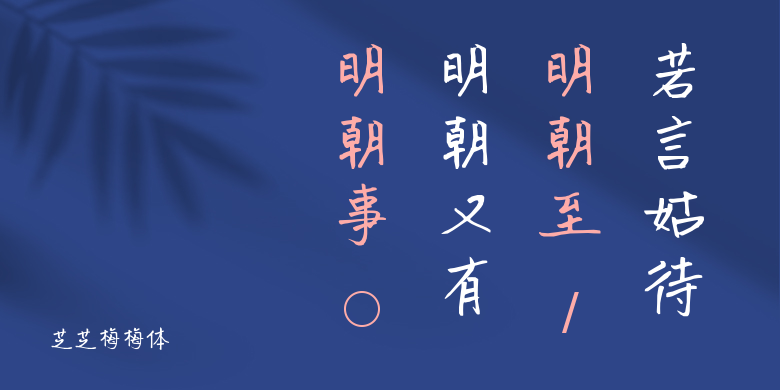
芝芝梅梅体
芝芝梅梅体,这款字体结构工整、笔画清晰,兼顾美观与易读性,适用于标题、正文、海报、包装、LOGO 等多种场景。字形优雅稳定,风格百搭耐看,适配日常排版与创意设计,让文字呈现更舒适、更具质感。芝芝梅梅体一笔一画,皆是细节,以均衡的比例、流畅的线条打造舒适视觉体验,字形端正大气,风格简约现代。无论是商业设计、品牌宣传还是日常排版,都能轻松驾驭,让文字更有格调与力量。芝芝梅梅体字体下载。